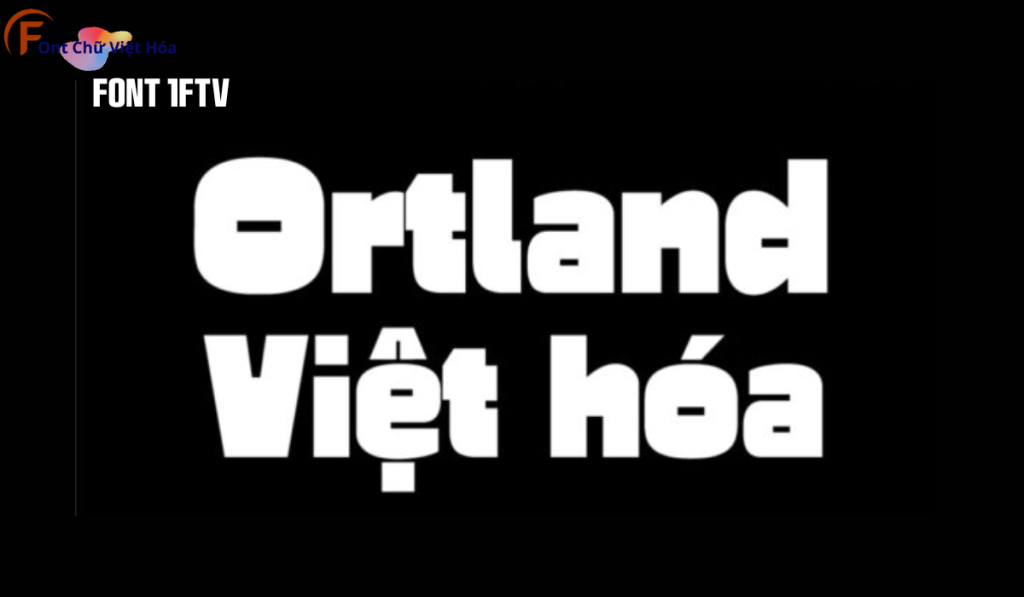
Font 1FTV Ortland
Tác giả: 1FTV Design
Bộ Font: 1FTV
Font 1FTV Ortland là một font chữ độc đáo, thuộc bộ 1FTV, nổi bật với phong cách sans-serif hiện đại và các đường nét đậm, cá tính. Thiết kế của 1FTV Ortland tập trung vào sự mạnh mẽ và dễ đọc, đặc biệt phù hợp cho các thiết kế đòi hỏi tính thẩm mỹ cao như poster, logo, và tiêu đề. Với tỷ lệ chữ cân đối và các đường nét rõ ràng, font này tạo ra ấn tượng thị giác mạnh mẽ và giúp tối ưu hóa không gian trong thiết kế. Font này cũng đã được Việt hóa, mang đến sự linh hoạt và tiện dụng cho các dự án thiết kế bằng tiếng Việt